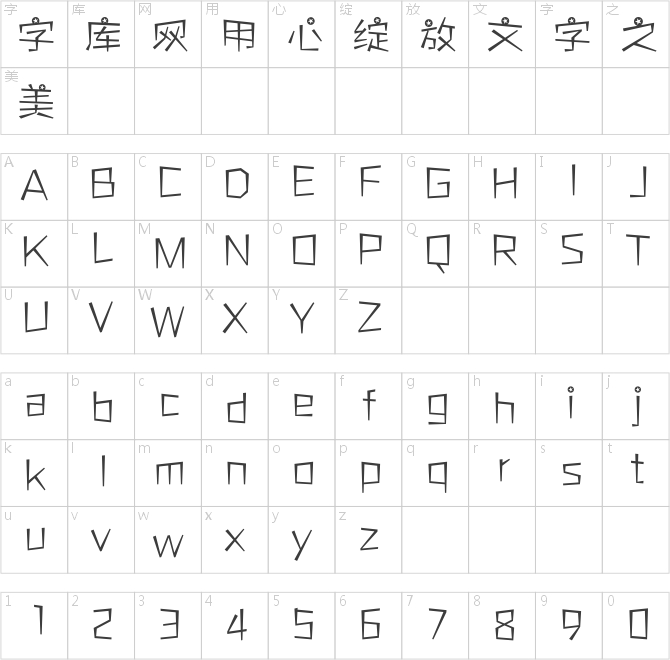
字體名稱: 方正酷牛體 簡
方正酷牛體 簡 ExtraLight
方正酷牛體 簡 ExtraLight介紹
方正酷牛體 簡 ExtraLight字體字庫是一款讓人賞心悅目、百看不厭的中文字體,適合各類廣告和產品包裝設計應用,字體大小1.98MB,格式為ttf字體,上傳用戶是happy,作者/版權方為方正字庫